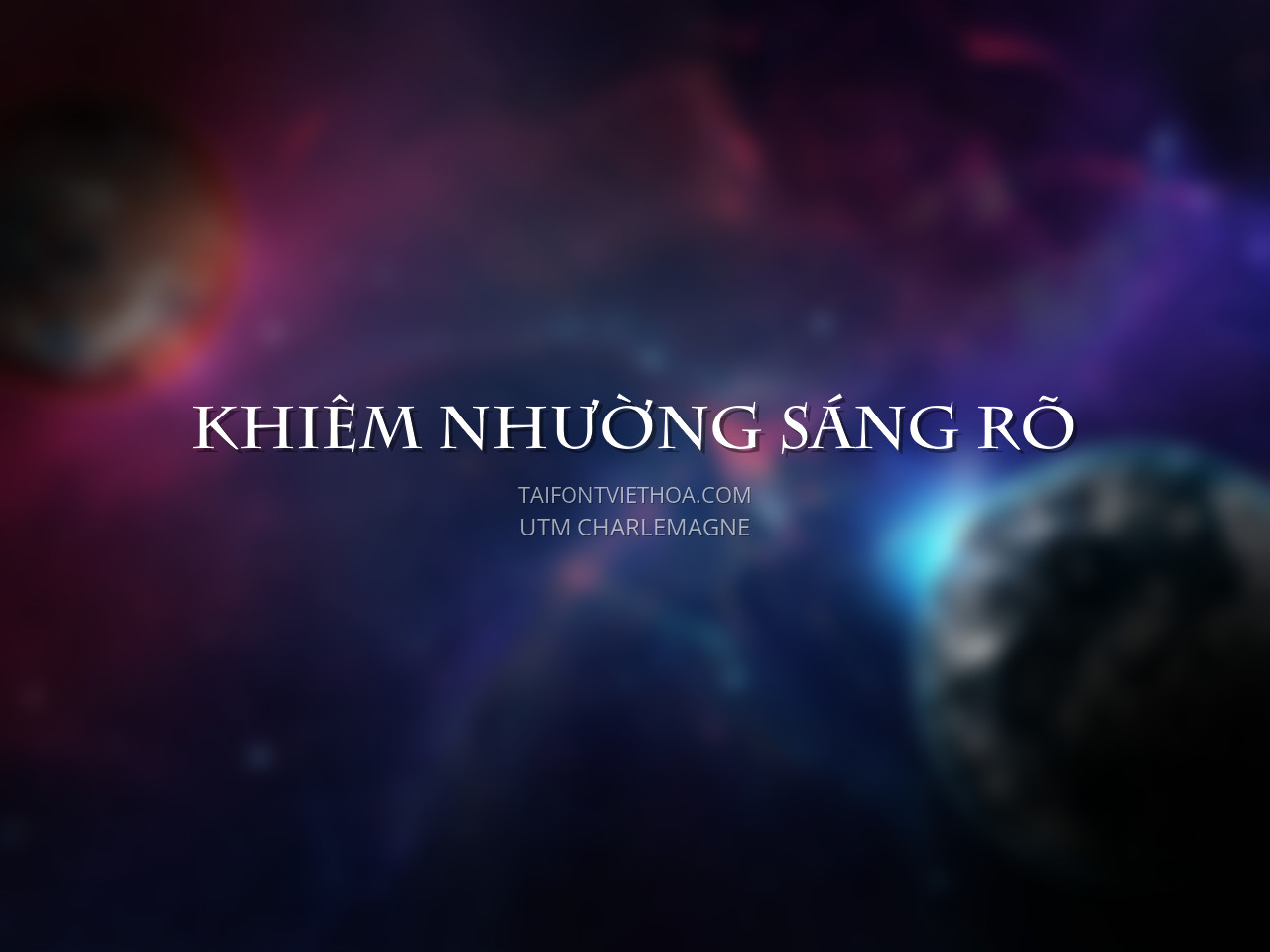
Giới thiệu về font UTM Charlemagne
UTM Charlemagne là phiên bản Việt hóa của font Charlemagne – một kiểu chữ serif cổ điển, trang trọng và sang trọng, lấy cảm hứng từ phong cách chữ viết thời Trung Cổ và Phục Hưng châu Âu. Font gốc nổi bật với các nét chữ có chân (serif) dày dặn, tỉ lệ cân đối và thiết kế uy nghiêm, phù hợp cho các dự án thiết kế mang tính lịch sử, nghệ thuật và thương hiệu cao cấp. Phiên bản Việt hóa đã được hoàn thiện để hỗ trợ đầy đủ tiếng Việt cùng hơn 200 ngôn ngữ khác, mở rộng khả năng ứng dụng trong các dự án thiết kế chuyên nghiệp và nghệ thuật.
Đặc điểm thiết kế và ứng dụng của UTM Charlemagne
UTM Charlemagne sở hữu cấu trúc serif với các nét chân chữ dày dặn, độ tương phản cao và thiết kế cân đối, tạo nên sự uy nghiêm và dễ đọc. Font phù hợp cho cả nội dung văn bản dài và tiêu đề nổi bật. Font còn tích hợp nhiều ligature và glyph thay thế giúp tăng tính linh hoạt trong thiết kế.
Font thích hợp sử dụng trong thiết kế sách, tạp chí, thiệp cưới, danh thiếp, bao bì sản phẩm sang trọng và các ấn phẩm thương hiệu cao cấp. Các ngành nghề phù hợp gồm: xuất bản, thời trang, nghệ thuật, tổ chức sự kiện, giáo dục và thiết kế nội thất.